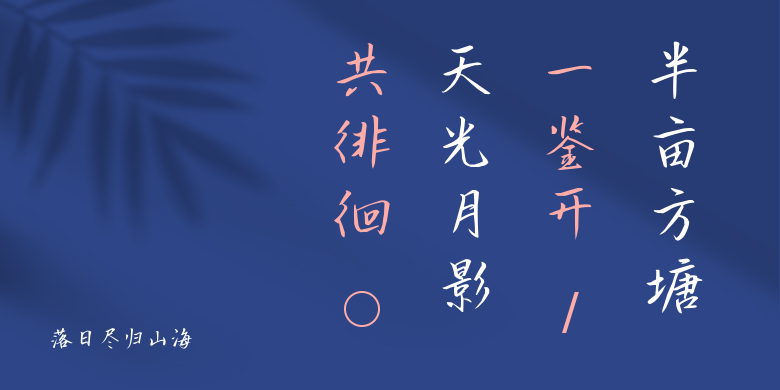
落日尽归山海
落日尽归山海,这款字体结构工整、笔画清晰,兼顾美观与易读性,适用于标题、正文、海报、包装、LOGO 等多种场景。字形优雅稳定,风格百搭耐看,适配日常排版与创意设计,让文字呈现更舒适、更具质感。落日尽归山海一笔一画,皆是细节,以均衡的比例、流畅的线条打造舒适视觉体验,字形端正大气,风格简约现代。无论是商业设计、品牌宣传还是日常排版,都能轻松驾驭,让文字更有格调与力量。落日尽归山海字体下载。